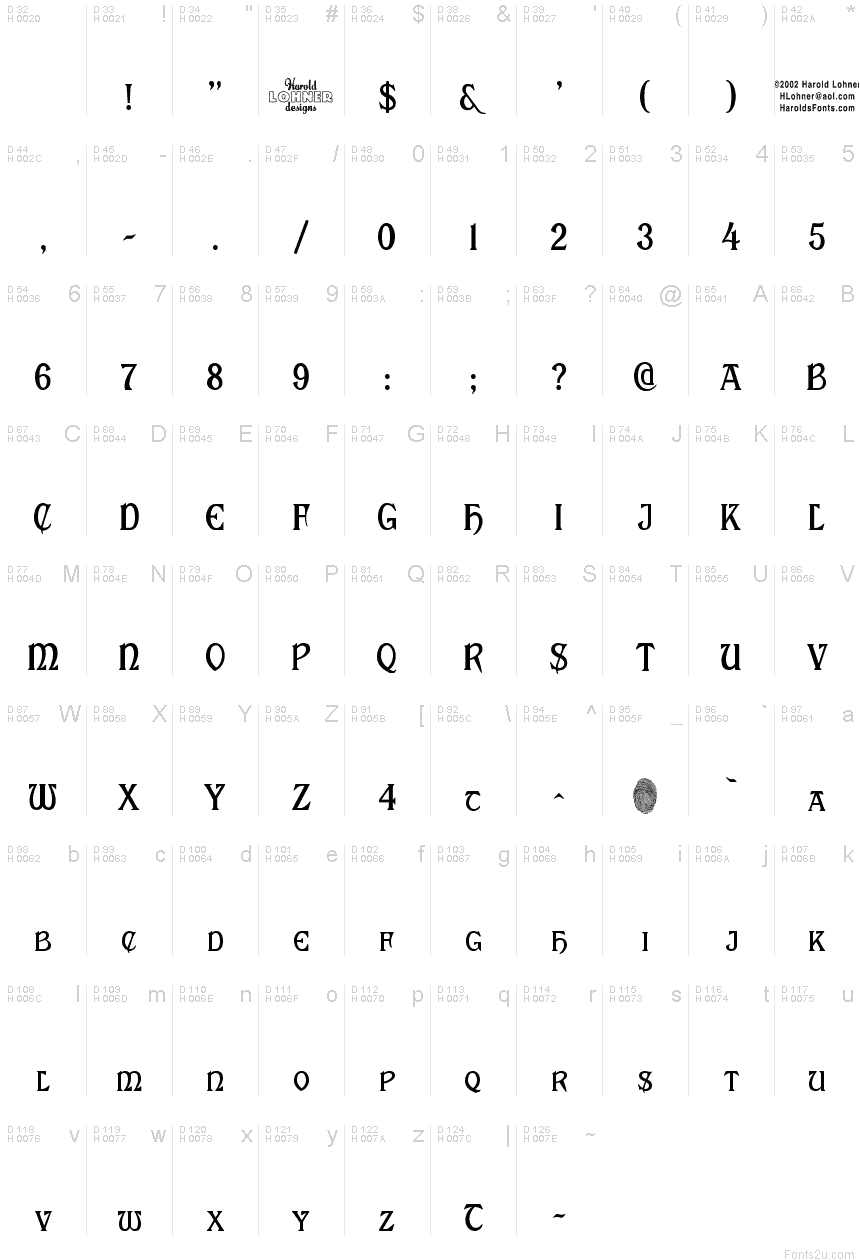
Roosevelt
Roosevelt, darmowy font Art Nouveau autorstwa Harolda Lohnera, przywraca elegancki krój liter znany z zabytkowych tabliczek na pianinach i organach. Litery łączą w sobie krzywizny o wysokim kontraście ze zwężającymi się, nieco teatralnymi pociągnięciami, powracając do kilku charakterystycznych motywów: zaokrąglonych miseczek, ostrych łączeń i długich ogonków, które nadają wyrazom liryczny rytm przełomu wieków.
Krój pasuje do opakowań, tytułów na plakatach, brandingu muzycznego, okładek książek i stylizowanej typografii, gdzie ten klimat dawnych lat może podkreślić przekaz. Jako darmowy font, Roosevelt sprawdza się również w monogramach, krótkich tekstach na okładkach i planszach tytułowych, ponieważ te szerokie zakończenia i miękkie, owalne formy najlepiej prezentują się, gdy mają przestrzeń do oddychania.
Roosevelt computer font v 2.0 ©2002 Harold Lohner " HLohner@aol.com " www.haroldsfonts.com Based on the classic font used on Aeolian pianos and organs. Formerly called Cabaletta.